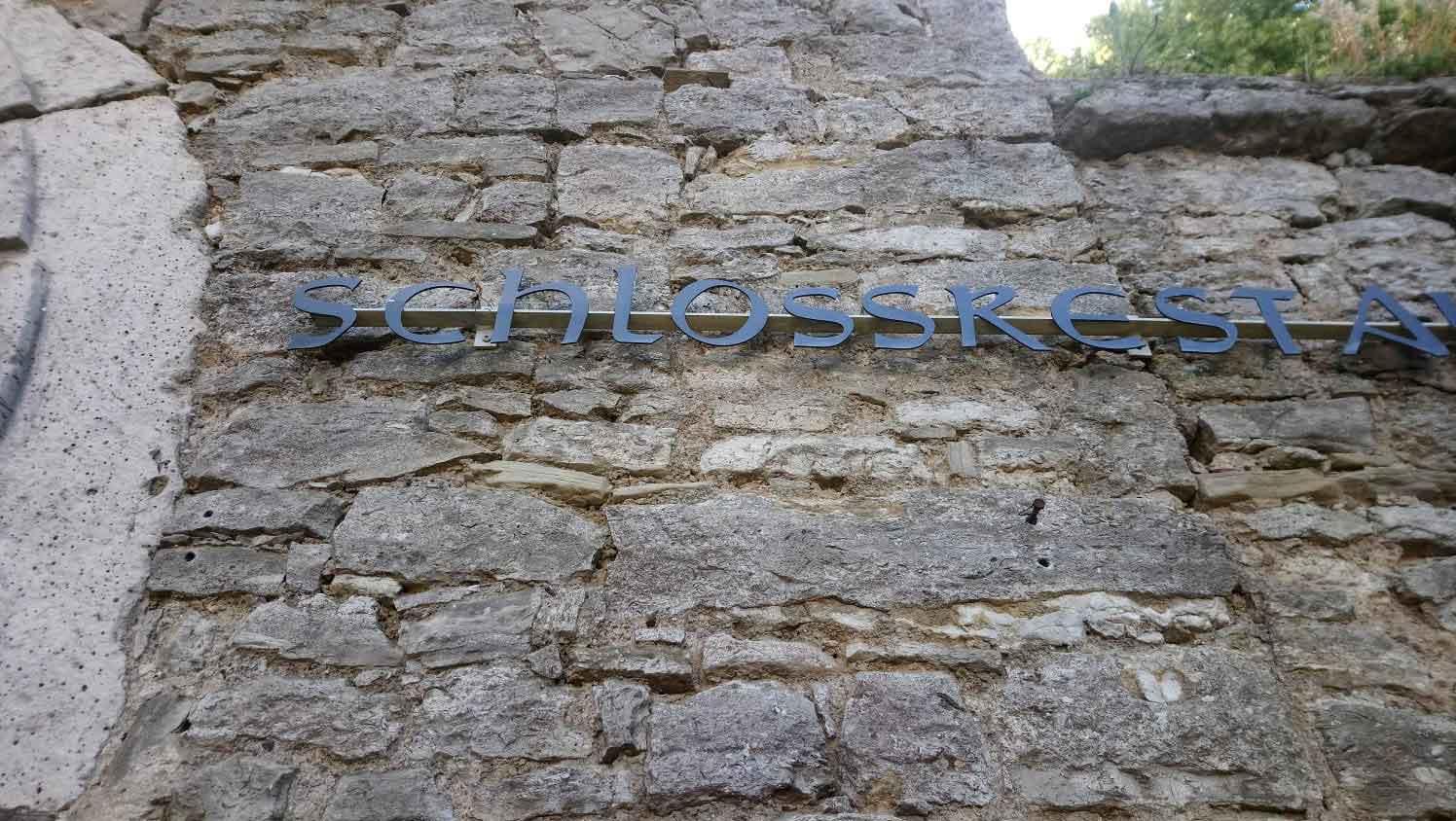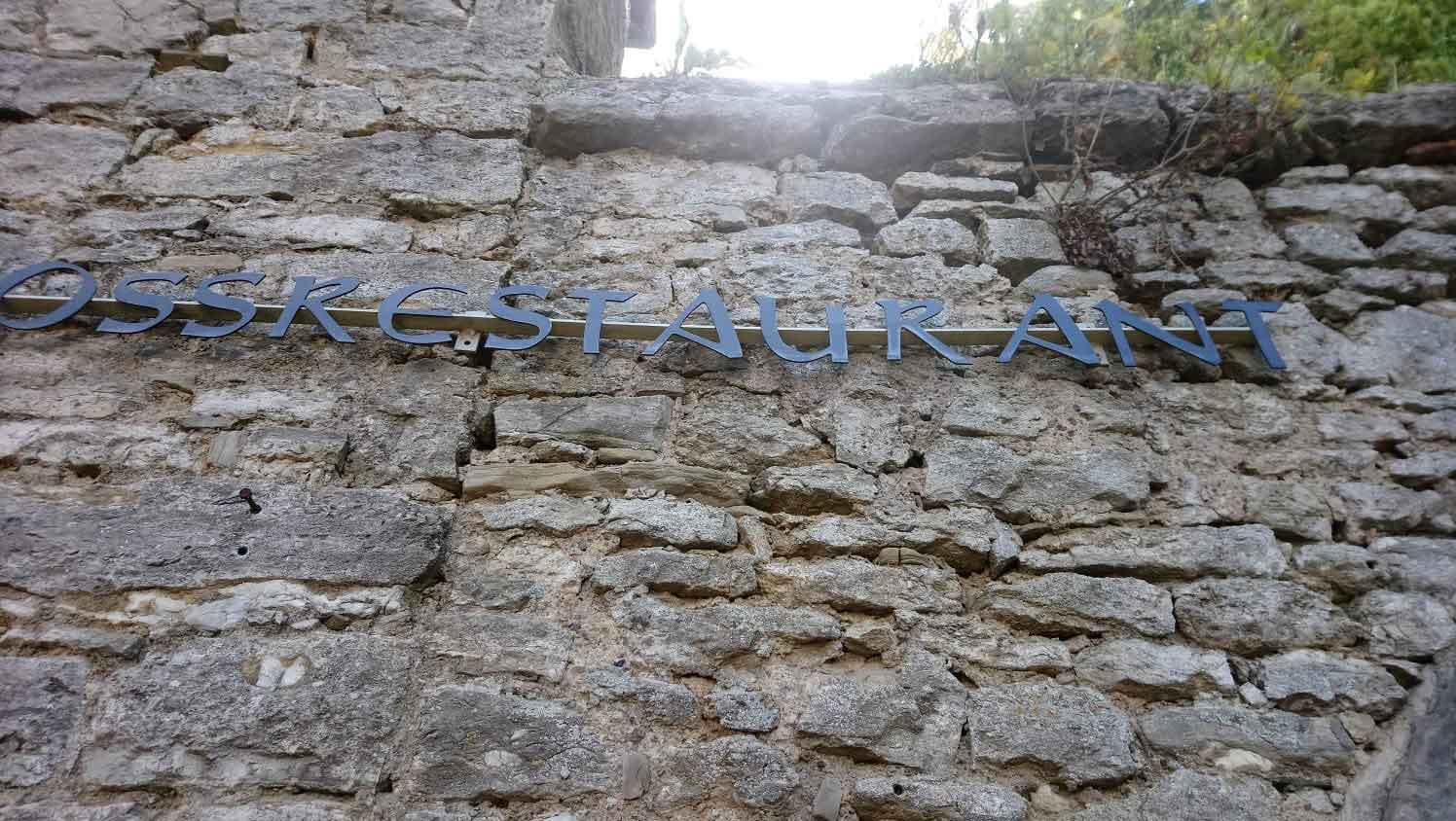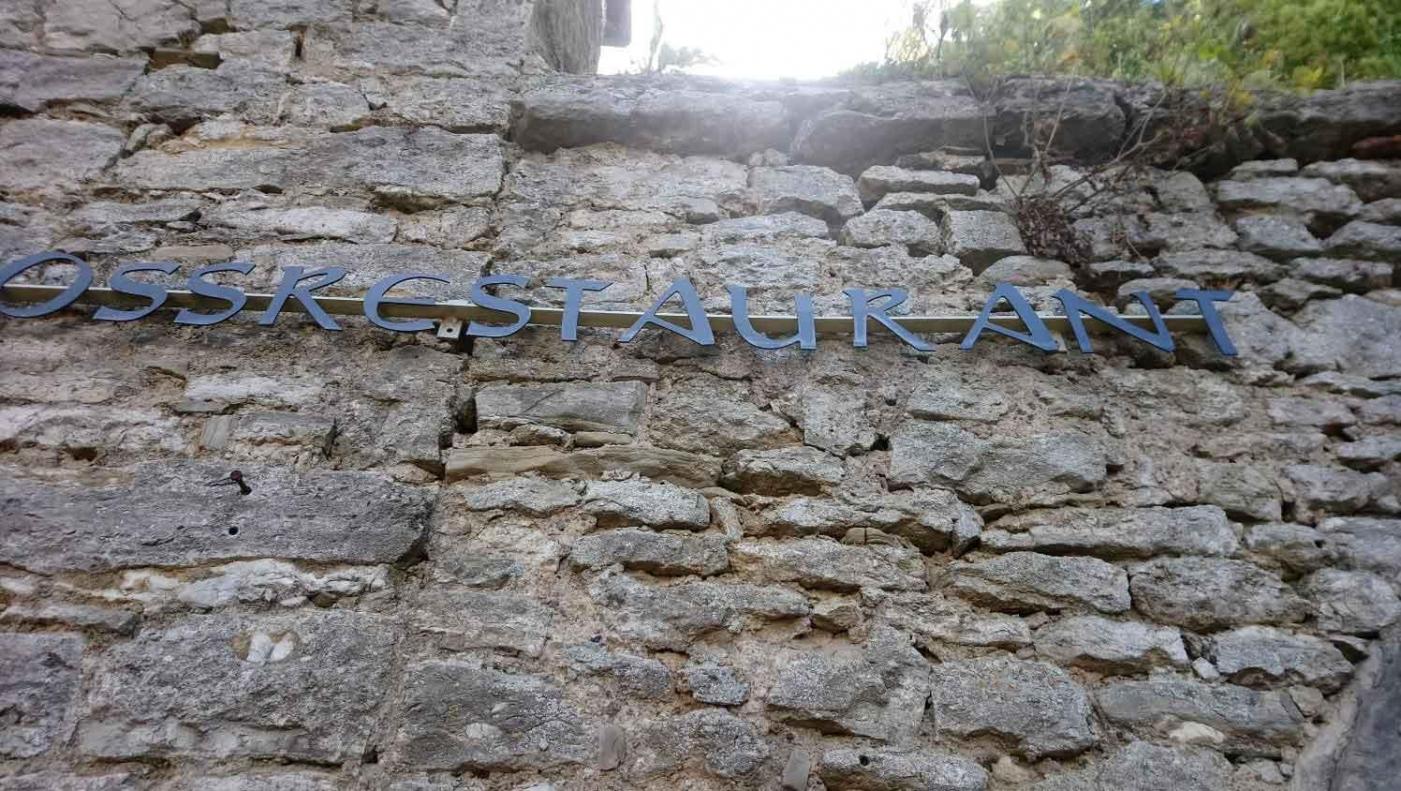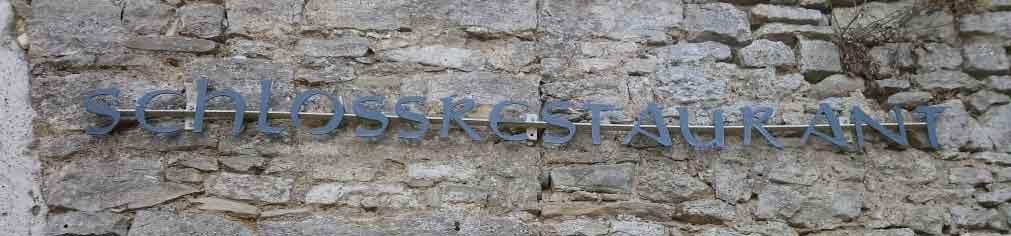
Schrift von Schlossrestaurant
Wäre es da ohnehin nicht besser, es neu zu zeichnen – falls nur die Buchstaben SCHLORETAUN benötigt werden?
Warum gehst du davon aus, dass es einen Font dazu gibt :-?Gleiche Details bei gleichen Buchstaben kann hier auch einfach heißen, es wurde die gleiche Schablone benutzt …
Kann es sein, dass das »A« gespiegelt aufgeschraubt wurde?
Glaube ich nicht, da der Strichkontrast ja richtig ist. Ich denke eher, dass da was nicht verstanden wurde oder komisch interpretiert wurde – spräche auch dafür, dass das irgendwer extra gezeichnet hat und vielleicht was Eigenes ™️ einbringen wollte.
Es ist in allen Details eine Katastrophe.
Kann man so erstmal schwer beurteilen, wegen der erstaunlichen Lesbarkeit in Grau auf Grau :hammer: Aber das Kerning ist mindestens so kreativ wie das A …
Erstens, weil mir Details bekannt vorkommen zu scheinen und zweitens, weil es insgesamt so schlecht gemacht ist, dass ich nicht erwarte, dass man den Extra-Aufwand von Lettering betrieben hätte.
In den wesentlichen  Elementen ist das die Wald-und-Wiesen-Unziale, wie ich sie in der Schule gelernt habe. Vielleicht ist hier einfach nur ein Schriftmusterbuch geplündert worden?
ich hab mal in meiner umfangreichen Sammlung gälischer / irischer Fonts rumgesucht - so ein "griechisch" anmutendes A hab ich nirgends gefunden, die hatten dann immer noch ne Verschnörkelung oder Strichunterbrechung.
Das U, das oben nicht gleichmäßig abschliesst, gibt es auch, ebenso das H und L, die aus der oberen Schriftlinie "ausbrechen", aber nie passte ALLES zusammen - ich glaub fast, da hat jemand aus vielen Schriften die jeweils unmöglichsten Buchstaben zusammengesucht...
weil mir Details bekannt vorkommen zu scheinen
Gesehen hab ich die auch schon irgendwo, wahrscheinlich nur die Grundformen in verschiedenen Schriftarten. Ich hätte die spontan bei dafont verortet, so in der Richtung "Ketisch", "Gälisch" …